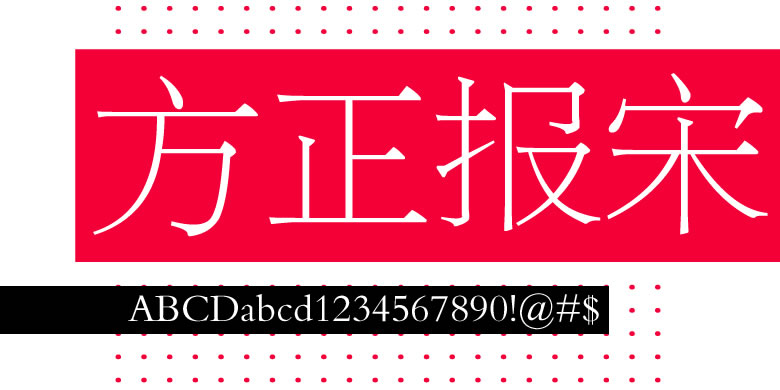
品牌:方正字库设计师:华蔚苍发行时间:1996字库编码:大陆简体(GB2312-80)、大陆繁体(GB12345-90)、简繁扩展(GBK)、港台地区(BIG-5)分类:宋体
1964年,北京新华字模厂以华蔚苍为代表的字体设计师们,参考日本的“秀英体”,为《人民日报》设计了正文字体“641体”(即报宋体)。该字体笔画偏细,横竖粗细相近,这是一款根据铅印工艺专门设计的报纸正文用字。此外,由于它的中宫放松,字面很大,所以可以略微缩小字号来增大版面的容量。方正报宋是“报宋”字稿的数字化产品,今天仍然被《人民日报》等多家报纸采用。